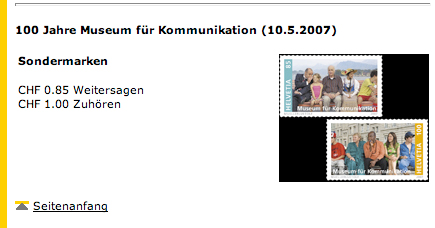
schrift, die nur bei bewegung lesbar ist?
gibt es eigentlich eine schrift, die so konzipiert ist, dass man sie erst gut lesen kann,
wenn man sie vor dem auge hin und her oder hoch und runter bewegen muss?
kennt da jemand was in der art? type, die erst mit bewegung erkennbar wird...
Einen schnurgeraden Tipp habe ich dir leider nicht zu bieten, aber vielleicht hast du ja die Muße, etwas zu recherchieren?
Die Schweizerischen Bundesbahnen SBB haben vor einigen Jahren mal die technische Machbarkeit abgeklärt (oder abklären lassen), im Gotthardtunnel (Nike???)Werbung so geschickt in einer Serie von Einzelbildern zu platzieren, dass dem Betrachter durchs Zugsfenster ein Film präsentiert würde. Als Beleuchtungsquelle musste das Licht ausreichen, das aus den Zugfenstern auf die Tunnelwände fällt. Wenn ich mich recht erinnere, hat auch ein Mathematikprofessor der ETH Zürich mitberechnet ... die Sache wurde – als machbar eingestuft – aus Sicherheitsgründen in irgendeine Bundes(schub)lade gesperrt.
Norbert, genau daran hatte ich auch gerade gedacht, an diese raffinierte Werbeaktion. Die war aber nicht nur geplant, die gab’s auch wirklich! Ich kann mich gut daran erinnern, ich glaube, sie war in einem Tunnel auf der Strecke Basel–Bern platziert. Das ganze funktionierte, glaube ich, aber nicht nur mit dem Licht des Zugs … »Motionposter« ist wohl das Stichwort.
Bei uns (München) hatten sie diese vorbeilaufende Werbung einfacher realisiert...mit einem sehr langen Band von lauter Bildschirmen, deren Anzeigen mit der Geschwindigkeit der S-Bahn synchronisiert waren.
... verwende geschäftlich Briefmarken der Schweizerischen Post, die in einem speziellen Verfahren hergestellt wurden, das sich "Lentikularraster" nennt. Bei Bewegung sieht man verschiedene Bilder in einem Ablauf. Am Beispiel dieser Briefmarken (Musée de la communication 1907–2007) ein paar Menschen, die sich wahlweise etwas erzählen oder einander zuhören.
Funktioniert auch mit Schrift, ist aber ziemlich komplex in der Entwicklung ...
Gibts in ähnlicher (gröberer?) Form schon lange und wird öfters auch für große Werbekampagnen genutzt (James Bond, American Airlines etc.).
edit: Genau! "Wackelbilder" nennt man die auch (hat mir eben der Norbert Pautner geflüstert. Danke!)
»Wissen Sie, dass die Reklametafeln früher höchstens sieben Meter lang waren? Aber die Wagen sausten so rasch daran vorbei , dass man die Tafeln in die Länge ziehen musste, damit sie überhaupt noch wirkten.«
Wichtiges Thema seit der industriellen Revolution.
cool, danke für die zahlreichen antworten, da sind ja irre sachen dabei, die wasserfasllaktion hatte ich auch schon beinahe wieder vergessen, wahnsinn. im grunde suche ich eine schrift, die den betrachter dazu bringt sich bzw. die schrift zu bewegen, und dabei in bewegung kommt. also schon am ehesten in richtung wackelbilder, aber die sind auch schon sehr ausgelutscht und auf jeder postkarte mit kitschigen motiven zu bekommen.
aber ich glaub mehr als das oder neonleuchtröhren (kenn ich garnicht, muss ich mal googlen) fällt mir auch nicht ein... hm
das sind keine neonleuchtröhren. das sind wahrscheinlich led- oder
lcd-systeme an die ist irgendwas befestigt was man in die hand nehmen kann
und durch kreisbewegung werden damit wörter in der luft erzeugt.
ähnlich sind langzeitbelichtungen, da gibts ja auch massig leute die mit
einer taschenlampe wörter schreiben und das per lzb knippsen. da
stand vor einigen monaten auch mal was in der page.
aachhhsooo, das meinst du, sowas, interaktiv sozusagen, man muss dann erst etwas schreiben... hmm... auch nicht ganz das, was ich suche, text soll scvhon vorhanden sein, aber erst lesbar sein indem man ihn bewegt, vorher ist noch nicht alles erkennbar.. jaja, ich weiss, vorstellungen hat die frau...
Diese Handstäbe enthalten nur eine einzelne Reihe LEDs. Auf diesen werden in Sekundenbruchteilen nacheinander die Spaltenmuster angezeigt, die auf einem normalen LED-Display nebeneinander stehen würden. Wenn man nun den Handstab seitlich bewegt, werden die Zeichen sichtbar. Je schneller man bewegt, desto höher die Zeichenbreite.